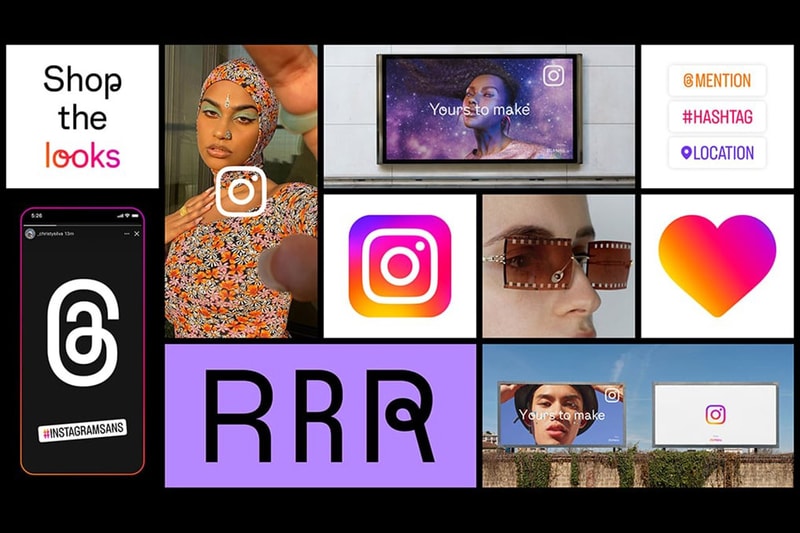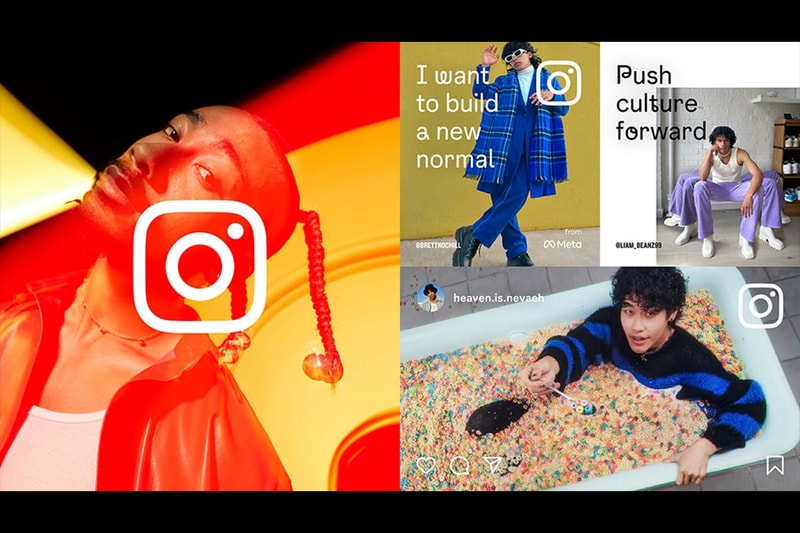
Instagram Merombak Logo dan Bikin Font Baru
“Visual refresh”.
Instagram ngumumin kalau mereka baru aja merombak visual identity-nya.
Perombakan itu mencakup logo mereka di aplikasinya, perubahan warna, layout dan design systems, dan penambahan font baru.
Secara bentuk, logonya sendiri nggak mengalami perubahan berarti sejak tahun 2016, namun kalau dilihat lebih detail, warna gradasi di dalamnya diubah biar keliatan makin vibrant dan fresh. Dalam pembuatannya, mereka pake 3D modeling process.
Buat font barunya, Instagram menghadirkan typeface yang dikasih nama Instagram Sans. Typeface ini nantinya bisa dipake sama para users baik di Stories, Reels, maupun lainnya. Font ini sendiri dibikin dengan berkolaborasi dengan ahli bahasa dari berbagai belahan dunia, buat nyediain desain fontnya dalam berbagai bahasa, termasuk Arabic, Thai, dan Japanese.
Instagram juga nge-refresh layoutnya jadi lebih simple dan bikin design system yang lebih nonjolin konten dan bakal nge-highlight self-expression dan kreativitas para usersnya.
Menurut Instagram, perombakan ini dilakuin supaya users-nya bisa punya experience yang lebih menyeluruh dan inklusif dalam membuat maupun mengonsumsi konten-konten yang ada.